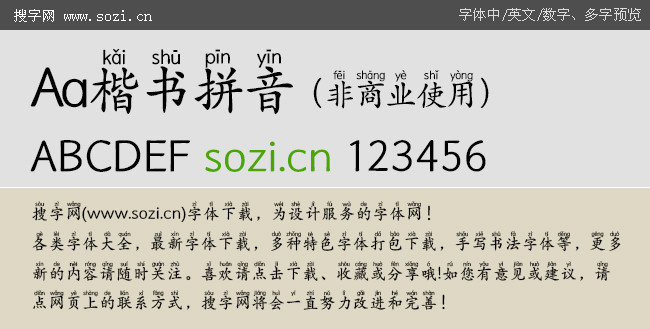
Aa楷書拼音
搜字網(wǎng)給大家提供一款A(yù)a楷書拼音(非商業(yè)使用)中文字體下載,該字體是一款簡潔的楷體字體,字體空間分布均勻,筆觸適中,書寫端正。適合書裝設(shè)計(jì)、包裝設(shè)計(jì)、海報(bào)設(shè)計(jì)等應(yīng)用(此字體為個(gè)人非商用版,商用可以聯(lián)系QQ:1006760504)。